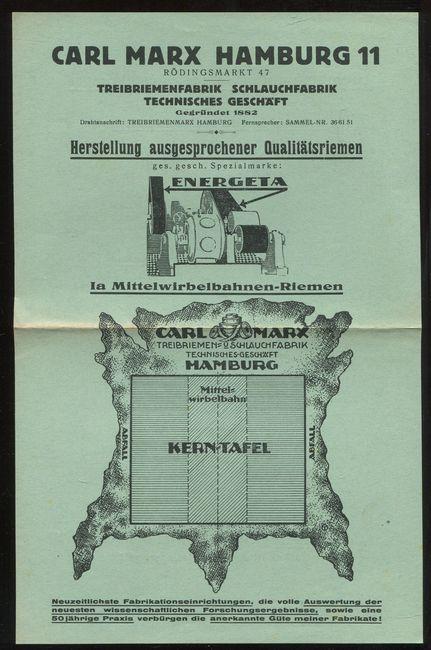
Nachteile eines Schlafwanderers.
Klingt nach einem spannenden Titel für ein Buch oder ein klassisches Musikstück.
OT, aber nicht ganz: Ich muss gerade wieder mal Rätsel erfinden und suche dazu auch Anagramme ... zu Sachsen-Anhalt kam dies dabei heraus: Haschnasental.
Aber das nimmt man doch nicht auf Nase :oops: Das spritzt man doch, oder … :mrgreen:
Haftbuchstaben kämen dazu in Beugehaft …
Das Wort ist typografisch ungeschickt gesetzt ...
Die Autor-E-Flexion beugt mit einem elektronisch gesteuertem Gerät den Autor selbst, während er schreibt, das beugt Rückenbeschwerden durch zu langes Sitzen vor ...
Spät am Abend steigt ein Reisender in ein Taxi. "Ich hab es eilig, dass im Hotel die Rezeption noch auf hat, dass ich meinen Zimmerschlüssel kriege..."
Der Taxifahrer gibt ordentlich Stoff, Erste Ampel ist Rot, er fährt durch, zweite Ampel rot, er fährt durch. Einige überfahrene rote Ampeln später ist eine Ampel grün, und der Taxifahrer stoppt.
Der Fahrgast, etwas verwirrt: "Warum halten sie hier, die Ampel ist doch grün, und ich habe doch gesagt, dass ich in Nacht-Eile bin..." "Ja", sagt der Fahrer, "aber nicht nur sie, also muss ich doch meine Kollegen durchlassen"
Hakennasennatter
Kam heute bei „Wer weiß denn sowas?“ vor und der Pflaume ist beim Vorlesen der Frage auch gestolpert. Wäre ich wohl auch wegen der vielen Doppelenns, die keine sind.
Doppelenns :-P
Baumhöhlenkrötenlaubfrosch
Konnte ich jetzt problemlos lesen – trotz der Länge und dass ich nicht mit Fröschen nicht auskenne.
Marx-Engels-Werke
Kein kniffeliges Wort in diesem Sinne, aber als ich die Überschrift las, dachte ich, die beiden waren doch keine Industriellen? Oder gibt es Industrieunternehmer gleichen Namens? Dass es um Bücher geht habe ich erst im Beitrag gerallt:oops::aschehaupt:
Immerhin gab es in Hamburg am Rödingsmarkt einst die Treibriemenfabrik Carl Marx. Leider konnte ich keinerlei Nachweise meht finden. Das Haus ist mittlerweile auch abgerissen.
Diese Firma hatte noch die typischen verschnörkelten Eisernen Firmennamen auf dem Dach wie es um 1900 üblich war. Ich war auch einmal in deren "Comptoir" weil ich Lederriemen-Verbinder für eine uralte Drehbank besorgen wollte. Ich fühlte mich in der Firma wie auf eine Zeitreise versetzt. Der Raum war durch eine hölzerne Trennwand unterteilt, in welcher uralte geätzte Glasscheiben  hatte, in der Mitte die Kunden-Klappe. Darin 2 Angestellte, die an einem uralten Schreibisch mit jeweils einer ebenso uralten, schwarzen mechanischen Schreibmaschine saßen. Der Gipfel der Moderne war ein W48-Telefon - ich besaß immerhin schon ein Handy... Auch trug einer der Angestellten doch tatsächlich noch Ärmelschoner...
Die hatten sogar neuzeitlichste Fabrikationseinrichtungen!